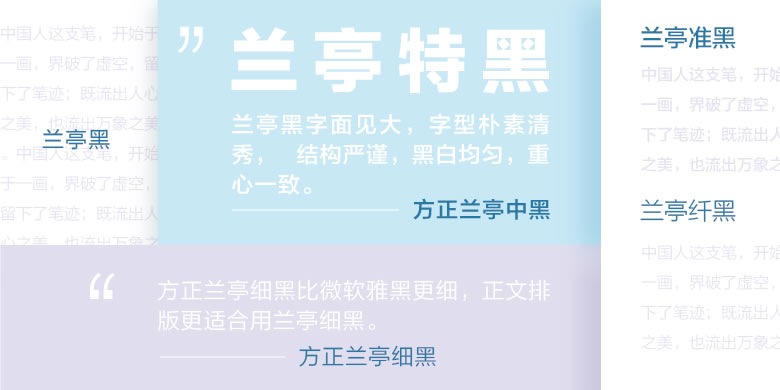
品牌:方正字库设计师:齐立发行时间:2006字库编码:大陆简体(GB2312-80)、大陆繁体(GB12345-90)、简繁扩展(GBK)、港台地区(BIG-5)分类:黑体
方正兰亭黑是国内最早专门为屏幕阅读设计、并由此衍生出的家族系列字体。兰亭黑字面大,字型朴素清秀,结构严谨,黑白均匀,重心一致;笔划制作精良,线条刚柔相济,简洁有力。阅读舒适流畅,有着鲜明的时代感。
2004年方正公司授权微软公司在Vista以后的Windows操作系统中使用方正兰亭黑和方正兰亭粗黑。在微软系统中,该字体被称为“微软雅黑”。
兰亭黑系列字体先后被美国高通公司的手机芯片、三星手机、华为手机、小米手机、苹果Mac OS Mountain Lion系统等产品使用。